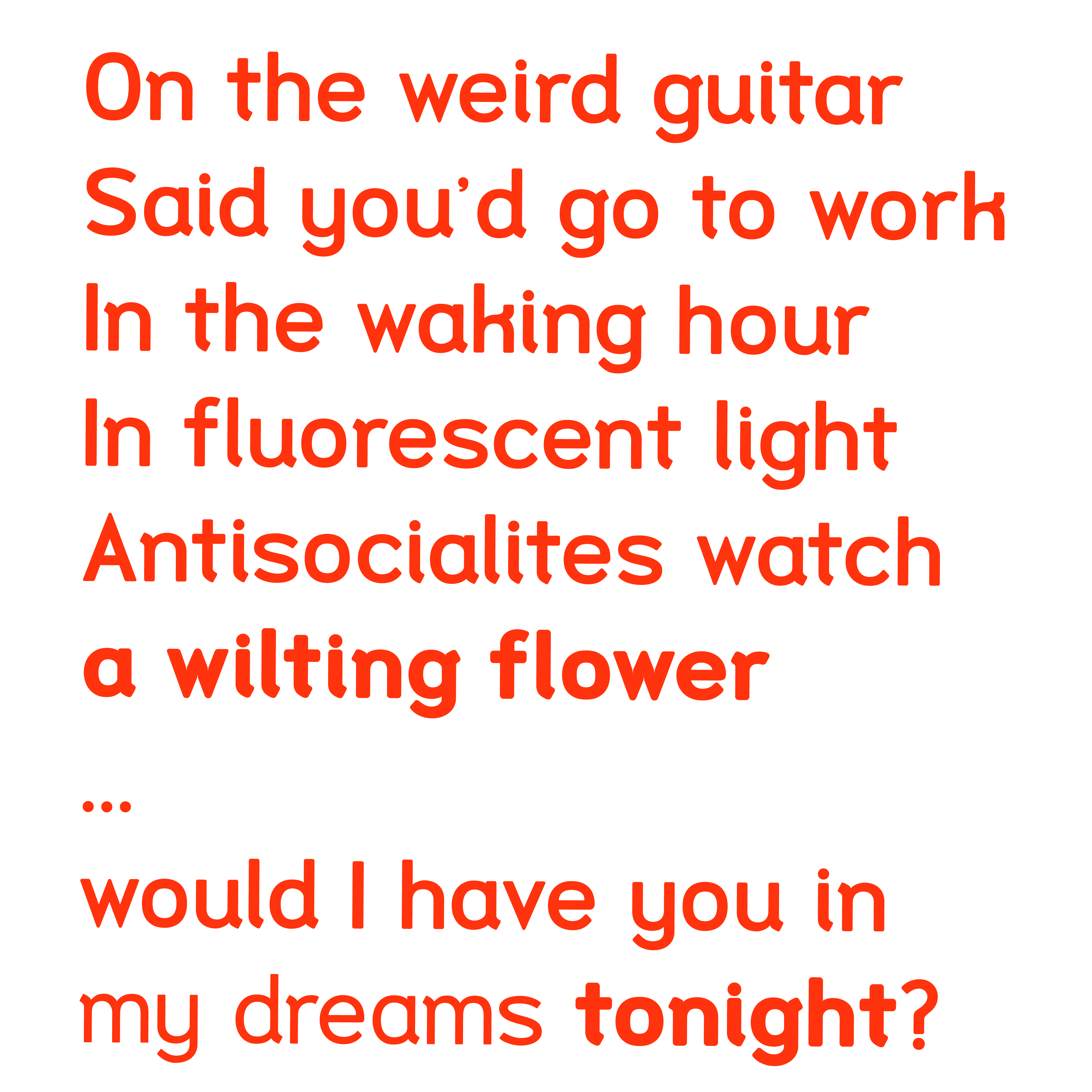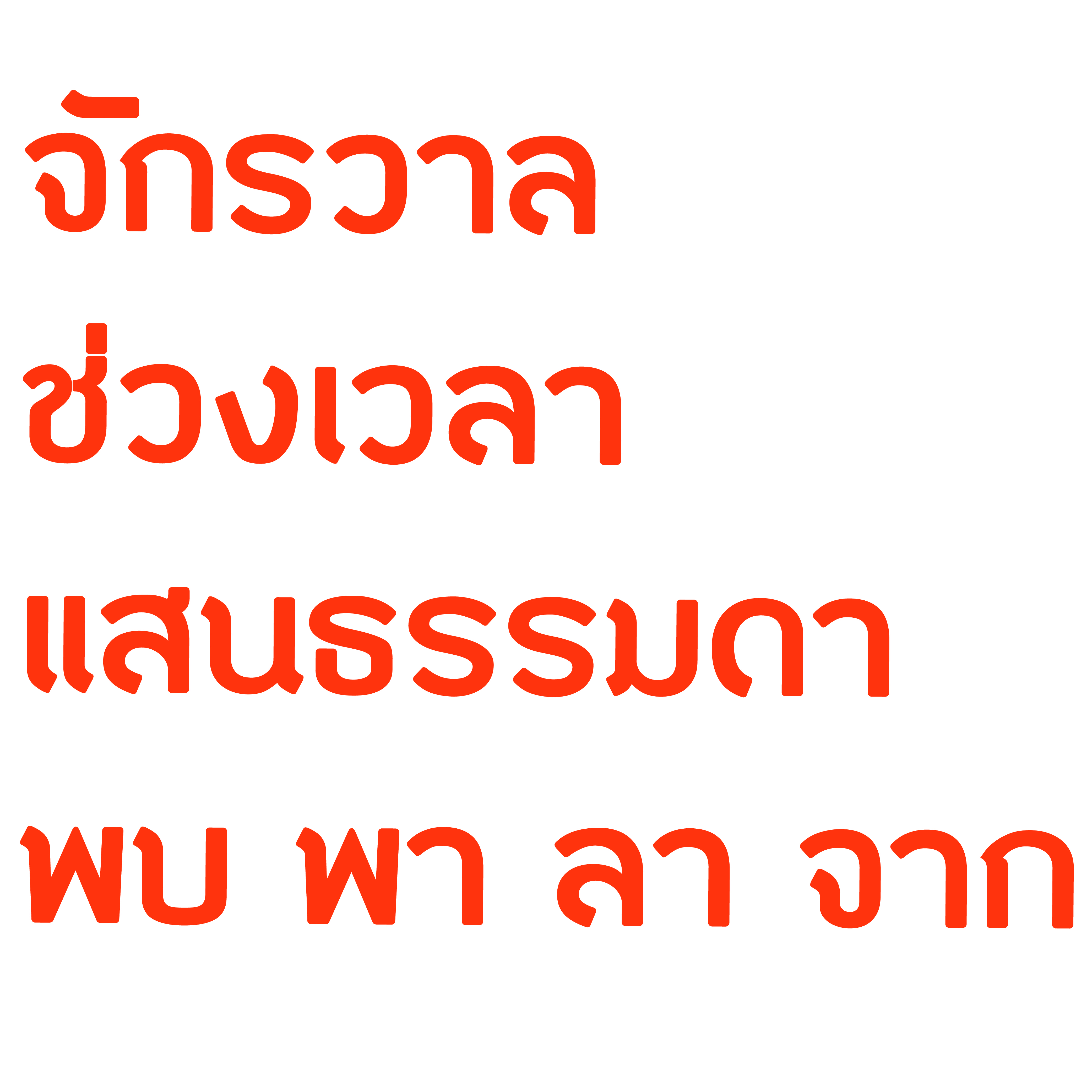
ปิ่น
พยายามให้เรียบ นิ่ง แต่มีความเป็นคน ผู้หญิงปิ่นปักผม
:12: มีหนาบางด้วย รอชมเลยครับ
ชื่อฟอนต์ : ปิ่น
เรียบ นิ่ง ธรรมดา แต่มีความเป็นคน ผู้หญิงปิ่นปักผม